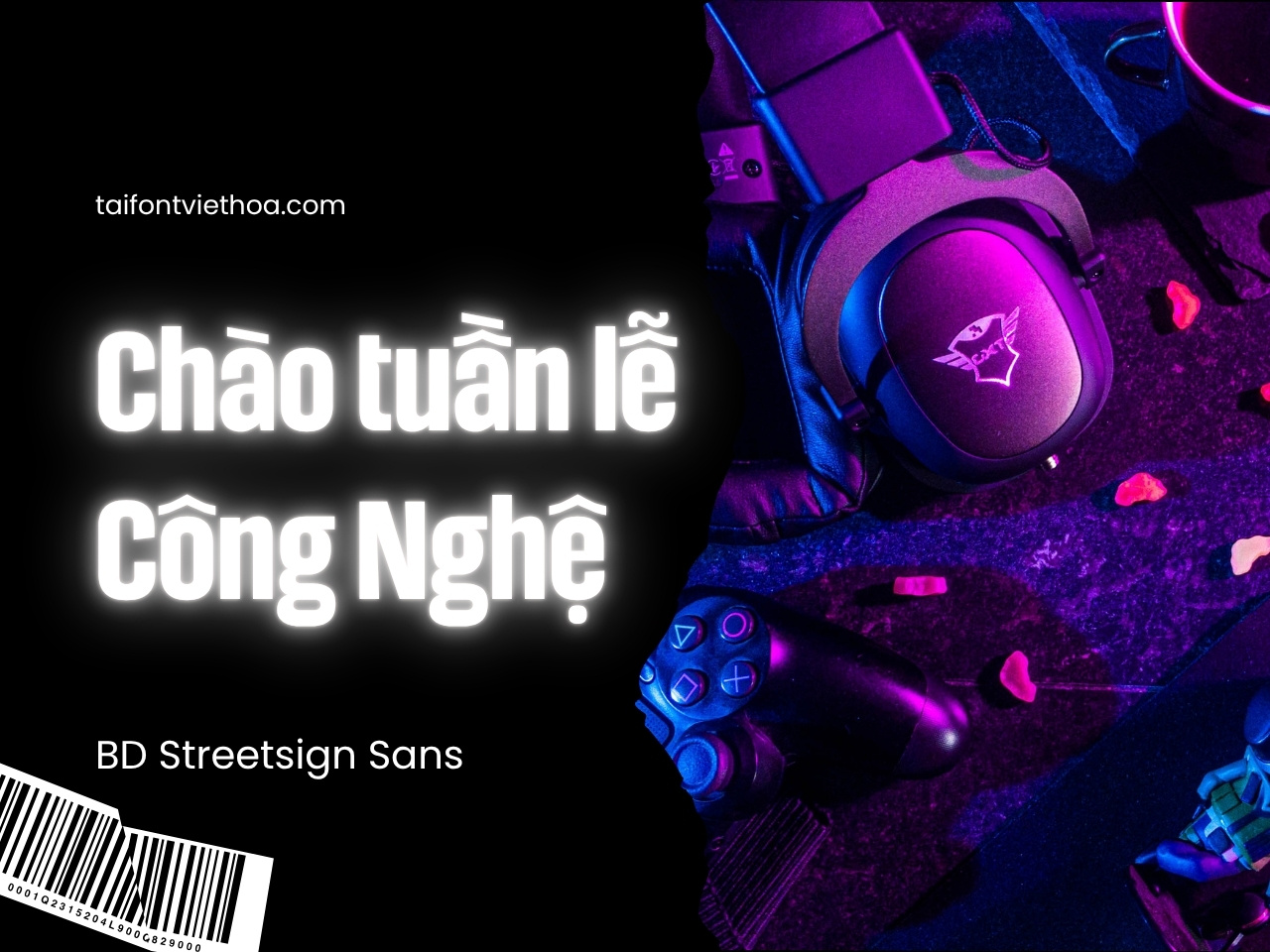
Font việt hóa Bd Streetsign Sans (Streetsign Sans 2.0 ) Font Tiếng Việt
Giới thiệu về font Streetsign Sans 2.0 và phiên bản Việt hóa
Streetsign Sans 2.0 là phiên bản nâng cấp mạnh mẽ từ font Streetsign Sans – một phông chữ sans-serif được thiết kế bởi Harry Dinh, lấy cảm hứng từ hệ thống biển báo giao thông và chỉ dẫn đô thị. Phiên bản mới được cải tiến về mặt hình thái học và khoảng cách chữ, giúp tối ưu khả năng hiển thị trong môi trường signage kỹ thuật số và in ấn. Font hỗ trợ đầy đủ hệ thống Latin mở rộng, bao gồm hơn 80 ngôn ngữ quốc tế và tiếng Việt có dấu.
Bản Việt hóa Streetsign Sans 2.0 do chính tác giả Harry Dinh thực hiện, đảm bảo chất lượng đường nét và khả năng tương thích cao với văn bản tiếng Việt. Tất cả dấu thanh, ký tự đặc biệt đều được thiết kế cẩn trọng, hài hòa với phong cách tổng thể của bộ font. Font này đã được taifontviethoa.com sưu tầm, kiểm tra kỹ lưỡng và chia sẻ lại nhằm phục vụ nhu cầu sử dụng trong các dự án thiết kế đậm tính kỹ thuật và nhận diện thương hiệu đô thị hiện đại.
Đặc điểm thiết kế và ứng dụng thực tế
Streetsign Sans 2.0 sở hữu cấu trúc sans-serif chắc chắn, hình khối gãy gọn và độ tương phản thấp, giúp hiển thị rõ nét trong cả điều kiện ánh sáng mạnh lẫn không gian nhỏ. Bảng chữ có tỷ lệ đều, độ cao chữ ổn định và khả năng căn chỉnh lưới layout tốt. Phiên bản này đặc biệt lý tưởng trong thiết kế hệ thống biển chỉ dẫn, signage công cộng, thiết kế branding kỹ thuật, các sản phẩm in ấn cho lĩnh vực bất động sản, công nghiệp và thành phố thông minh.
Không chỉ dành riêng cho kỹ thuật, Streetsign Sans 2.0 còn thích hợp cho các dự án UI/UX hiện đại, giao diện phần mềm, bảng hiệu showroom, bao bì sản phẩm công nghệ hoặc hệ thống thông tin kỹ thuật số trong ngành giáo dục, truyền thông, logistics và startup.